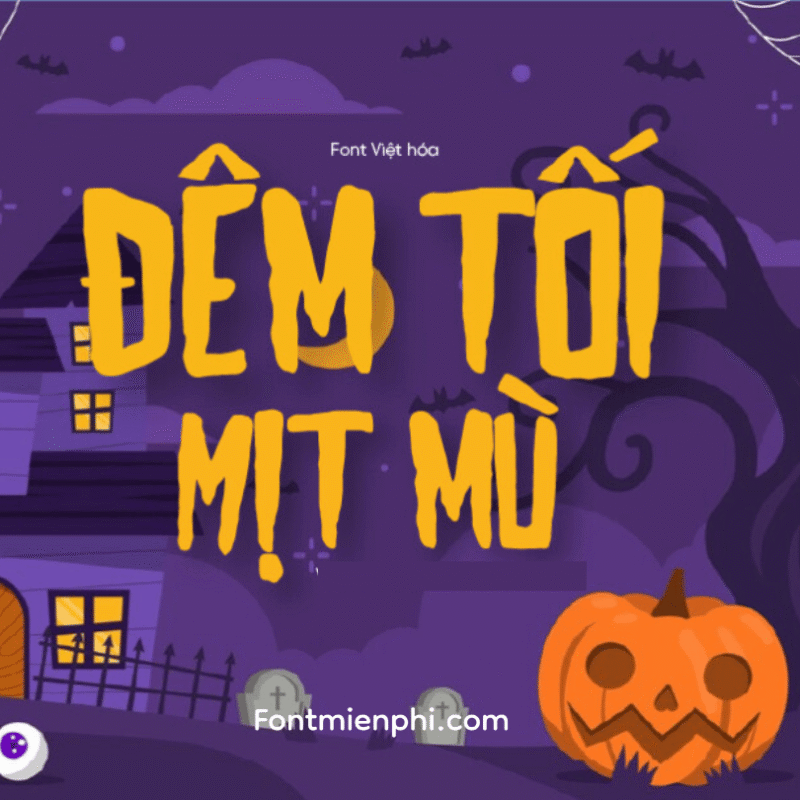
Font Việt hóa 1FTV VIP MAYHEM ,Font Halloween – Phông Chữ Halloween “Hỗn Loạn Kinh Hoàng”
1FTV VIP MAYHEM là font chữ Việt hóa cao cấp mang đậm chất kinh dị cực độ, được thiết kế để tạo ra những hiệu ứng “rùng rợn đến nghẹt thở”. Với phong cách hỗn loạn có chủ đích, font chữ này sẽ khiến mọi thiết kế Halloween của bạn trở nên ám ảnh khó quên.
ĐẶC ĐIỂM ĐỘC ĐÁO:
Hiệu ứng “máu me hỗn loạn” – Nét chữ vỡ vụn kết hợp vệt máu chảy
Hỗ trợ Unicode tiếng Việt đầy đủ – Dùng được cho mọi dự án cần độ kinh dị cao
3 phiên bản đi kèm: Regular (kinh dị nhẹ), Bloody (máu me), Chaos (hỗn loạn cực độ)
CÔNG DỤNG “GHÊ RỢN”: